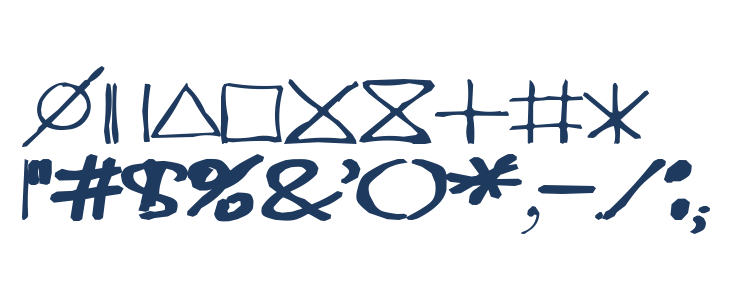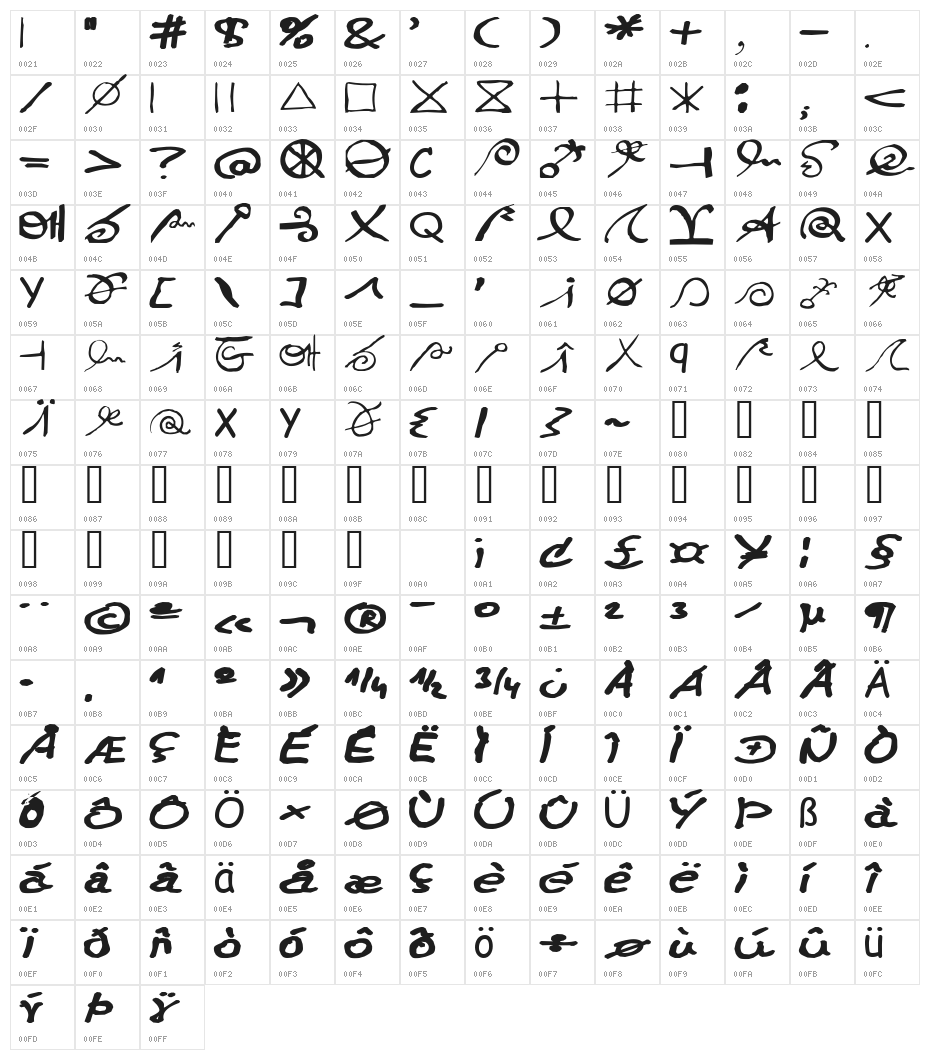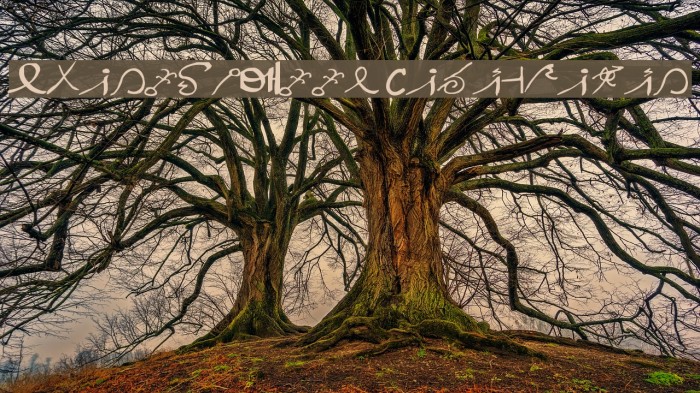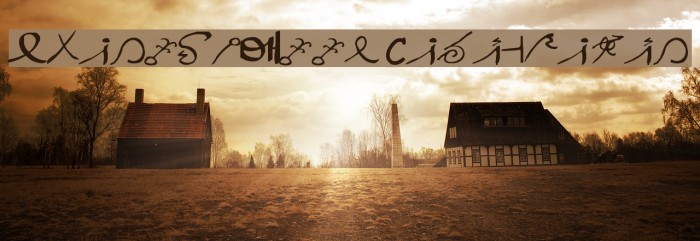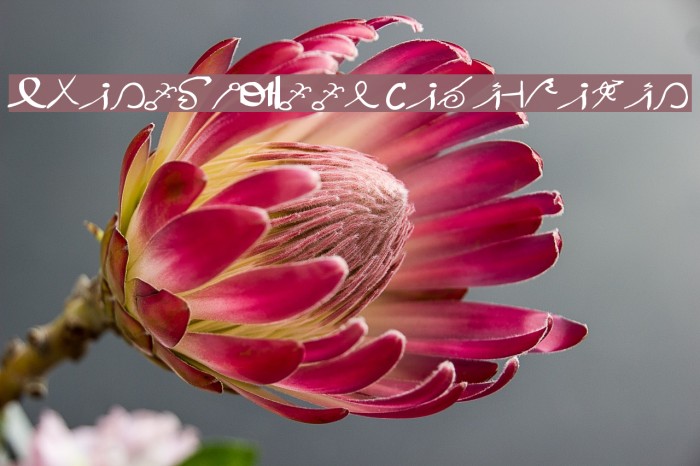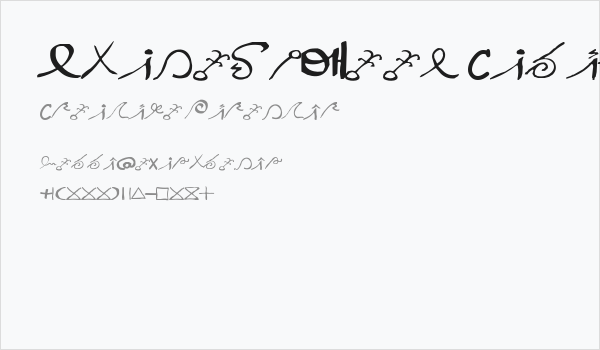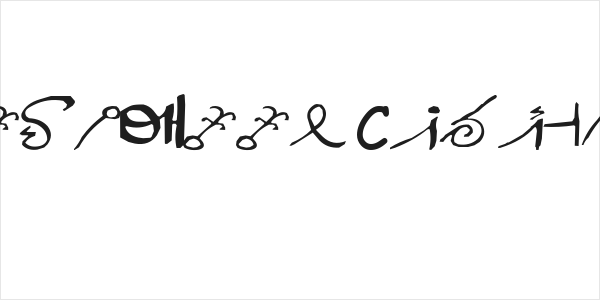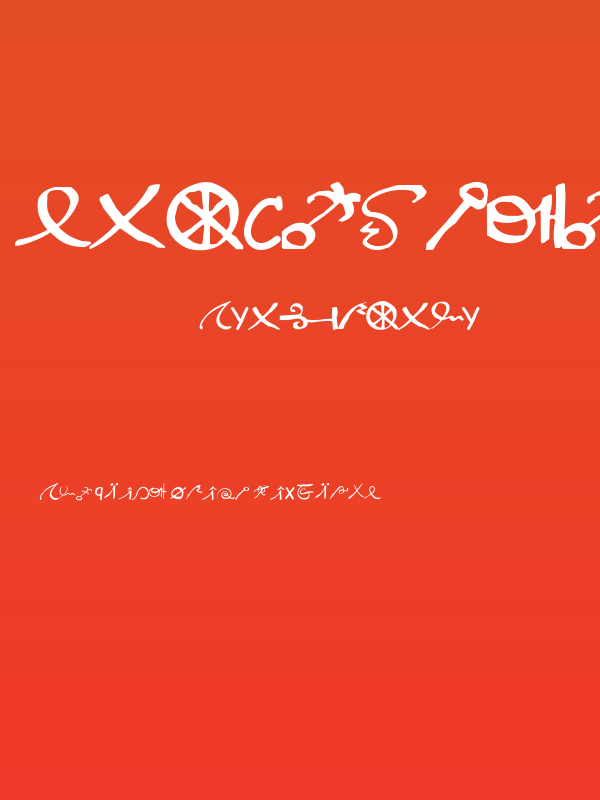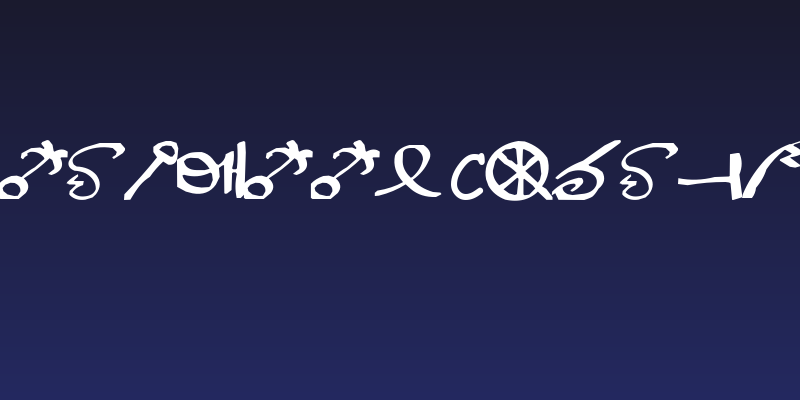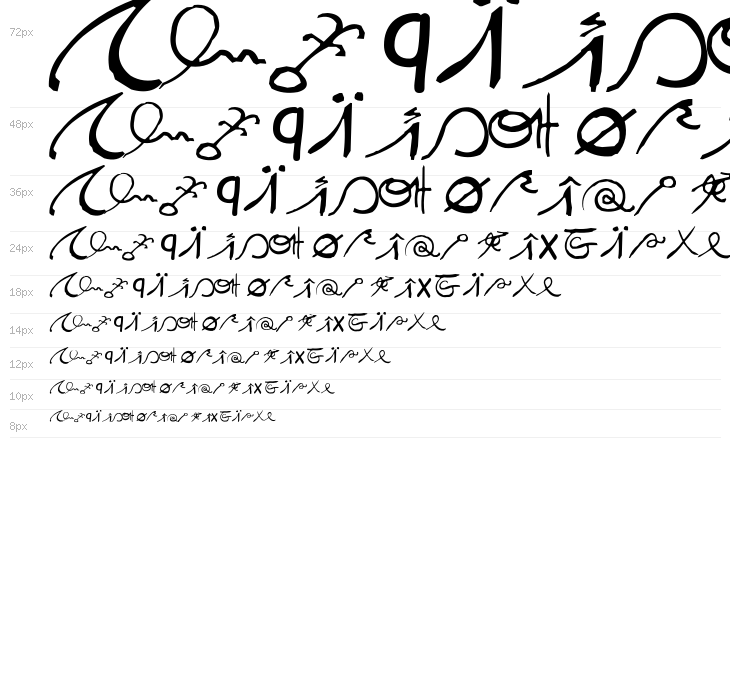
SpaceInKees Caligrafic Font
| Stile generale | Modern, Decorative |
| Caso d'uso | Logos, Artistic posters, Branding materials |
| Progetti proposti | Ideal for creative projects such as logo design, artistic posters, and branding materials that require a unique and expressive touch. |